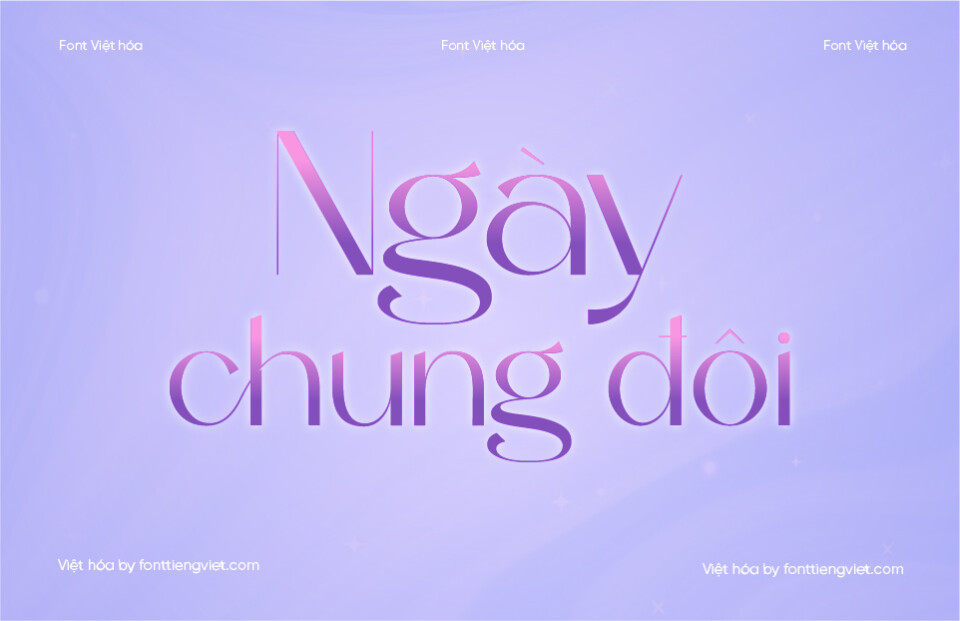
Font Việt hóa 1FTV VIP Ghakity
Tải Font Việt hóa 1FTV VIP Ghakity – Font Chữ Serif Sang Trọng Cho Thiết Kế
Giới thiệu về Font Việt hóa 1FTV VIP Ghakity
Trong thế giới thiết kế đồ họa hiện đại, việc lựa chọn một bộ Font Miễn Phí chất lượng luôn là ưu tiên hàng đầu của các nhà sáng tạo. Đặc biệt, bộ Font Việt hóa 1FTV VIP Ghakity đã trở thành một hiện tượng nhờ vẻ đẹp thanh lịch và tính ứng dụng cao. Đây là một phông chữ thuộc phong cách Serif (có chân) nhưng được cách điệu với những đường nét uốn lượn tinh tế, mang lại cảm giác vừa cổ điển vừa hiện đại. Phiên bản Việt hóa này giúp người dùng tại Việt Nam dễ dàng sử dụng trong các phần mềm thiết kế mà không lo lỗi hiển thị dấu tiếng Việt, đảm bảo tính thẩm mỹ đồng nhất cho toàn bộ văn bản.
Đặc điểm nổi bật của Font Việt hóa 1FTV VIP Ghakity
Thiết kế sang trọng và đẳng cấp
Bộ Font Việt hóa 1FTV VIP Ghakity sở hữu các đường nét thanh mảnh kết hợp với những điểm nhấn bo tròn mềm mại. Sự cân bằng giữa các nét thanh và nét đậm giúp phông chữ này trở nên cực kỳ thu hút thị giác. Điều này làm cho nó trở nên lý tưởng cho các dự án yêu cầu sự chuyên nghiệp và đẳng cấp như thiết kế logo thương hiệu cao cấp, thiệp mời sự kiện quan trọng hoặc các bìa tạp chí thời trang. Mỗi ký tự trong bộ font đều được chăm chút tỉ mỉ, giúp tạo nên một tổng thể hài hòa và đầy nghệ thuật.
Khả năng tương thích và tối ưu hóa
Một trong những lý do khiến Font Việt hóa 1FTV VIP Ghakity được yêu thích chính là khả năng hiển thị sắc nét trên cả ấn phẩm in ấn lẫn màn hình kỹ thuật số. Font đã được tinh chỉnh kỹ lưỡng về khoảng cách giữa các chữ cái (kerning) và độ cao của các ký tự (x-height), giúp người xem dễ dàng đọc nội dung ngay cả ở kích thước nhỏ. Bên cạnh đó, việc tích hợp đầy đủ các ký tự đặc biệt và dấu câu tiếng Việt giúp các bạn học sinh, sinh viên và thầy cô giáo có thể ứng dụng vào việc làm slide bài giảng hoặc báo cáo sáng tạo một cách thuận tiện nhất.
Ứng dụng thực tế của Font Việt hóa 1FTV VIP Ghakity trong thiết kế
Sử dụng trong truyền thông và quảng cáo
Với phong cách quý phái, Font Việt hóa 1FTV VIP Ghakity thường xuyên xuất hiện trong các chiến dịch quảng cáo mỹ phẩm, trang sức và nội thất. Khi kết hợp với các tông màu trung tính hoặc pastel, bộ font này giúp thông điệp truyền tải trở nên nhẹ nhàng nhưng vẫn đầy sức nặng. Ngoài ra, các bạn cũng có thể sử dụng nó để làm tiêu đề cho các bài viết trên mạng xã hội như Facebook hay Instagram để tăng sự tương tác và thu hút ánh nhìn từ người xem ngay từ giây đầu tiên.
Sáng tạo nội dung giáo dục và cá nhân
Trong môi trường học đường, việc thay đổi những phông chữ khô khan bằng Font Việt hóa 1FTV VIP Ghakity sẽ giúp các bài thuyết trình trở nên sinh động và chuyên nghiệp hơn. Bạn có thể dùng font này cho các tiêu đề lớn hoặc các câu trích dẫn truyền cảm hứng để tạo điểm nhấn. Đây là cách tuyệt vời để rèn luyện tư duy thẩm mỹ và kỹ năng trình bày nội dung một cách khoa học và đẹp mắt cho các bạn trẻ.
Kết luận về bộ font đẳng cấp